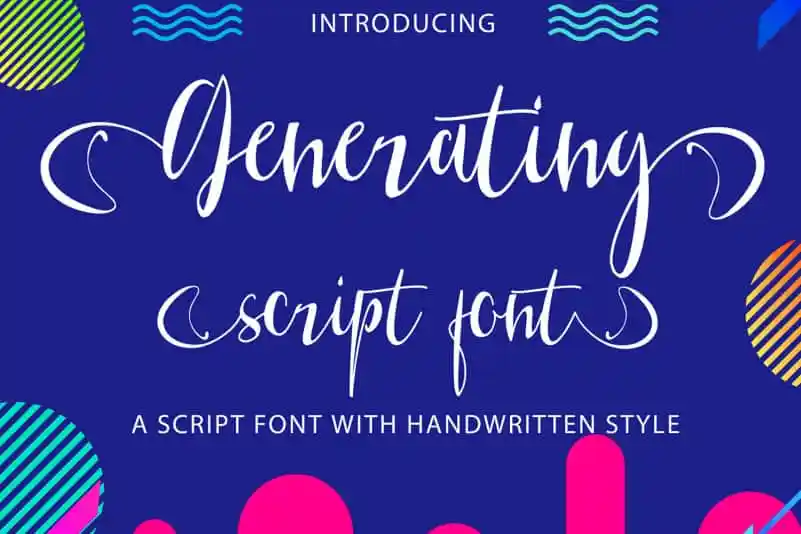
Generating Script Demo Font – Download Grátis
A ‘Generating Script Demo Font’ é uma fonte criada à mão que se destaca por sua simplicidade encantadora. Trata-se de uma fonte perfeita para qualquer projeto divertido, onde você pode explorar a capacidade única e peculiar de desenhar letras com um pincel leve e vibrante. Esta fonte é especialmente útil para designers criativos que buscam uma maneira lúdica de incluir elementos personalizados em seus trabalhos. O designer 177Studio certificou o fato de que a ‘Generating Script Demo Font’ possui ajustes kerning (entre-líneas) e matrices personalizadas, garantindo que todas as letras sejam perfeitamente integráveis entre si. Essas características tornam a fonte ainda mais versátil, adaptável para criar designs únicos com uma aparência harmoniosa e autêntica. Não importa o tipo de projeto em que você esteja trabalhando, a ‘Generating Script Demo Font’ é certamente um recurso gráfico indispensável.